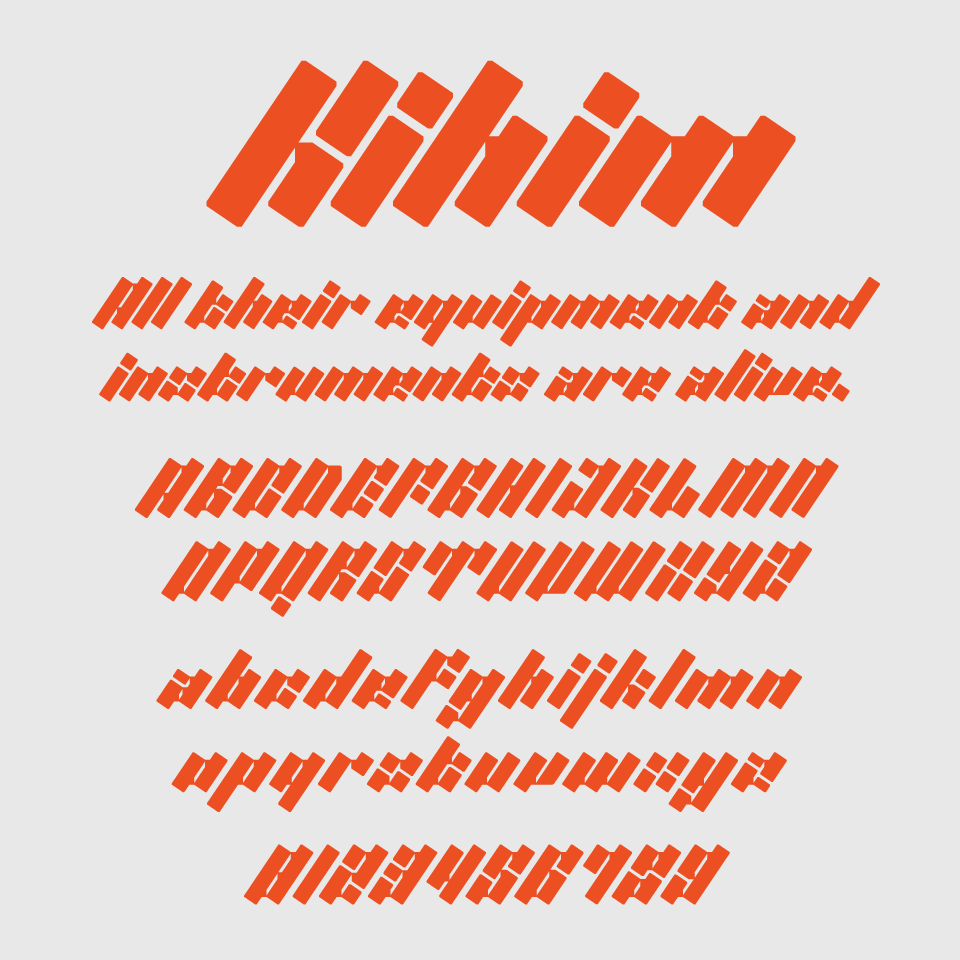
Kihimフォントは、斜めに傾いた極太ラインが特徴的な、力強く個性的なディスプレイ書体です。パッと見ではなかなか読めないので、視認性よりも造形のインパクトを重視しており、アート性の高い見出しや暗号チックなタイトルに向いているフォントです。
小文字にも幾何的な斜体のリズムがあり、文字間の一体感が独特の存在感があり、ユーモラスで遊び心も感じさせる遊びココロたっぷりなフォントです。